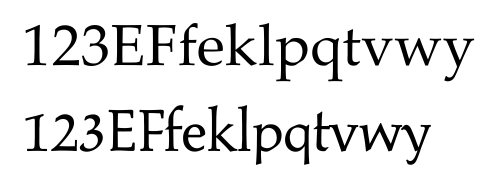
Orpheus endlich auch digital!
Regelmäßigen MyFonts-Besuchern und Canadatypefans wird es nicht entgangen sein, alle anderen würde ich gerne darauf hinweisen: Tiemanns großer Bleisatzklassiker Orpheus (und dessen kursive Ergänzung Euphorion) war m.W. merkwürdigerweise bisher noch nicht digital erhältlich. CanadaType hat ganz großes Kino draus gemacht, ich kann meine Begeisterung darüber nur schwer zügeln und empfehle deshalb wärmstens: http://new.myfonts.com/fonts/canadatype/orpheus-pro/
Wow ... Und beinahe geschenkt ...! Hoffentlich kommt bald ein Projekt welches die Anschaffung rechtfertigt ...! :biglove: Du Kursive ist der Knüller :-D
Schön, Danke für den Hinweis. Deine Begeisterung teile ich aber leider nicht.
Teilweise muß man sich die ursprünglichen Figuren aus verschiedenen OpenType-Stilsätzen zusammensuchen; das eingebogene h beispielsweise befindet sich zusammen mit Schwungformen in Stilsatz 5:
Andere ursprüngliche Zeichen fehlen vermutlich ganz — jedenfalls konnte ich sie der MyFonts-Vorschau nicht entlocken — so etwa der ft-Verbund und der Bindestrich:
Anstatt neue Figuren zu erfinden, hätten sie lieber erstmal alle ursprünglichen digitalisieren sollen. Und wenn man schon im Standardzeichensatz von der Vorlage abweicht, wünsche ich mir wenigstens einen Stilsatz, der alle Originalzeichen einstellt.
Leider dürfte die Schrift auch kaum textgrößentauglich sein. :-(
- schon im Bleisatz hat man die Orpheus als Textschrift eher im höheren Brotschriftbereich und größer - also so ab 12pt aufwärts gesetzt - vor allem in bibliophilen, meist relativ großformatigen Ausgaben (soetwas gab es früher wirklich mal) mit sehr splendid Platz, weil die Orpheus halt auch für so etwas Nobles, Vornehmes, Feierliches gemacht war und sich demzufolge in 8 oder 10 Punkt nur bedingt entfalten kann. Tiemann selber hat sie häufig so eingesetzt und mir gefällt gut, wie die kanadischen Kollegen Tiemanns oft handgezeichneten Abwandlungen für Titel- und Umschlaggestaltungen mit einbezogen haben in die vielen Buchstaben-Variationen. Eine ft-Ligatur ist dabei, wenn auch eine andere als im Bleisatz, nach dem Trennstrich müßte man schauen, irgendeiner wird sicherlich dabei sein ...
Ich finde es legitim und sehr schön, wenn eine fast vergessene Bleischrift auf diese gekonnte Art und Weise wiederentdeckt und zugänglich gemacht wird und finde es in Ordnung, wenn es keine absolute Replik der Bleisatzschrift ist. Das sind ja die meisten Digitalisierungen ohnehin nicht, und kann also auch nicht der Maßstab sein - wer druckt denn auch noch diese Fonts im Buchdruck? Es gibt übrigens überhaupt nur ganz wenige Fonts, die den originalen Bleisatzschriften tatsächlich bis ins letzte Detail entsprechen - und die meisten davon (die aus der Valdonega Aesthetic Line der Stamperia Valdonega) sind noch nicht einmal käuflich zu erwerben ...
vielleicht kann dieses Beispiel der Kanadier irgendeinen jungen ambitionierten Digitalschriftdesigner anregen, auch endlich die Kursive der Tiemann-Antiqua (die leider nur bei Linotype in zwei geraden Schnitten verfügbar ist) in die heutige Welt zu retten? Würde ich sehr begrüßen! Nach der Ingeborg vor nicht allzu langer Zeit und jetzt der Orpheus wäre das eine weitere geschlossene Lücke. Falls sich jemand hier angesprochen fühlen sollte - ich hätte durchaus auch noch ein paar andere Bleisatzschriften gern digital zur Verfügung, denen trotz hunderttausender Fonts der Weg ins Heute noch immer nicht gebahnt wurde, die es aber eigentlich verdient hätten ... Vorschläge (mit Schriftmustern unterschiedlicher Qualität) könnte ich bei Bedarf gerne liefern.
schade das der fette schnitt der orpheus nicht digitalisiert wurde, aber vielleicht folgt der ja noch.
die kursive orpheus wurde übrigens auch als euphorion geführt.
Es gibt übrigens überhaupt nur ganz wenige Fonts, die den originalen Bleisatzschriften tatsächlich bis ins letzte Detail entsprechen - und die meisten davon (die aus der Valdonega Aesthetic Line der Stamperia Valdonega)
kannst du da etwas genauer werden? welche fonts genau entsprechen bleisatzschriften bis ins letzte detail?
Nach der Ingeborg vor nicht allzu langer Zeit und jetzt der Orpheus wäre das eine weitere geschlossene Lücke.
die ingeborg (wir sprechen doch von der typejockeys ingeborg) basiert aber nicht auf einen bleisatzfont, oder?
1. Es gab m.W. nie eine kursive Orpheus in Blei, sondern immer nur die Euphorion als eigenständige Kursiv-Schrift, die aber immer als DIE passende Kursive zur Orpheus betrachtet und empfohlen wurde. Warum das so war, weiß ich nicht. In Blei schien mir die Orpheus deutlich weiter verbreitet zu sein als die Euphorion - das ist aber ein sehr subjektiver Eindruck, weil ich selber nur ein paar Kästen Orpheus hab, die Euphorion in Blei mir aber nie über den Weg gelaufen ist ... die hab ich immer nur in Schriftmustern gesehen.
2. In der Stamperia Valdonega in Verona wurde in den 90ern (ich weiß nicht wie lange) Bleisatzschriften nach dem Druckbild im Buchdruck digitalisiert. Diese Digitalschriften sollten dasselbe Schriftbild ergeben wie im Buchdruck gedruckter Bleisatz. Man ist also nicht von Zeichnungen oder Entwürfen ausgegangen, sondern vom Druckbild unter Beachtung beispielsweise des "Quetschrandes" beim Hochdruck. Meines Wissens wurden diverse Monotype-Klassiker wie Garamond, Baskerville und Dante (und noch ein paar andere) digitalisiert. An die Schriften kommt aber keiner ran, weil sie nur für Kunden der nicht gerade billigen Stamperia zur Verfügung gestellt wurden, die in der Stamperia gestalten, setzen und drucken ließen. D.h. diese Schriften durften das Haus nicht verlassen und wurden nie verkauft. Ich kannte mal einen, der an der Digitalisierung gearbeitet hatte. Und selbst er hatte nach eigener Aussage die Schriften nicht.
Diese Schriften sind also die m.W. einzig wirklich perfekten Repliken von Bleisatzschriften, weil sie das ursprüngliche Druckbild in den Offsetdruck übertragen.
Bei anderen ist es schon schwieriger und da müsste man jetzt einen Roman schreiben - es gab ja auch Bleisatzschriften gleichen Namens, aber unterschiedlicher Ausführung. Und welche Bleisatzfassung welcher Digitalfassung entspricht wäre ein weites Feld "vergleichender" Forschung. Es geistern beispielsweise ein paar Typoartdigitalisierungen aus undurchsichtigen Quellen durch die Welt (schon lange bevor E&F Typoart für sich entdeckt haben), die m.E. ziemlich genau die entsprechenden Bleisatzschriften von Typoart abbilden.